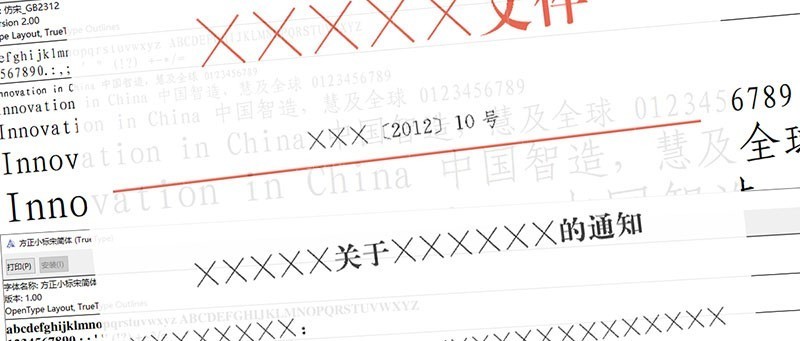
办公OA必备字体:仿宋GB2312、方正小标宋简体
按照《国家行政机关公文格式》规定:
行政机关公文的发文机关标识(即俗称的红头)推荐使用小标宋体字,用红色标识;公文标题应使用2号小标宋体字;公文主题词的词目应使用3号小标宋体字。而普通电脑一般未自带该字体,需手动下载安装。
按照《国家行政机关公文格式》规定:
行政机关公文的发文机关标识(即俗称的红头)推荐使用小标宋体字,用红色标识;公文标题应使用2号小标宋体字;公文主题词的词目应使用3号小标宋体字。而普通电脑一般未自带该字体,需手动下载安装。